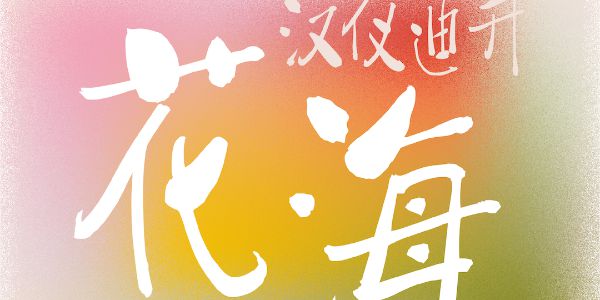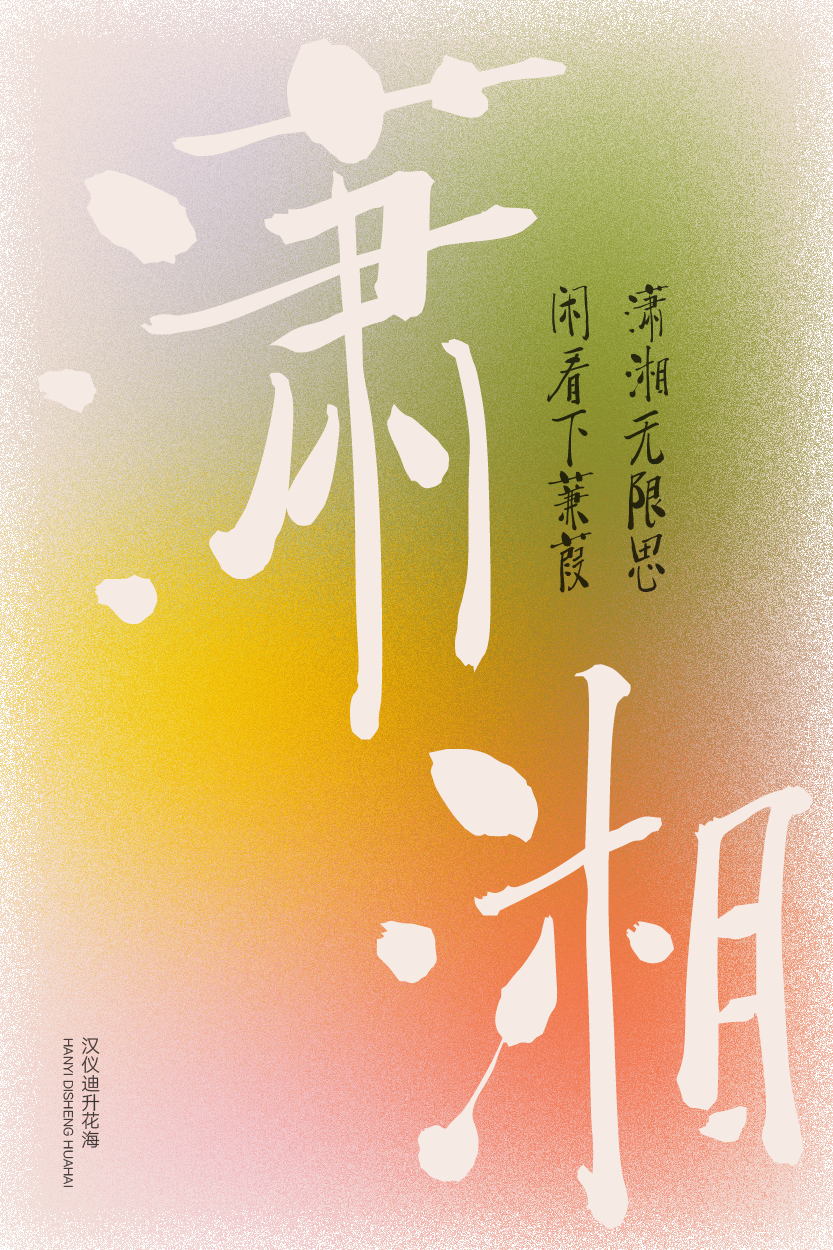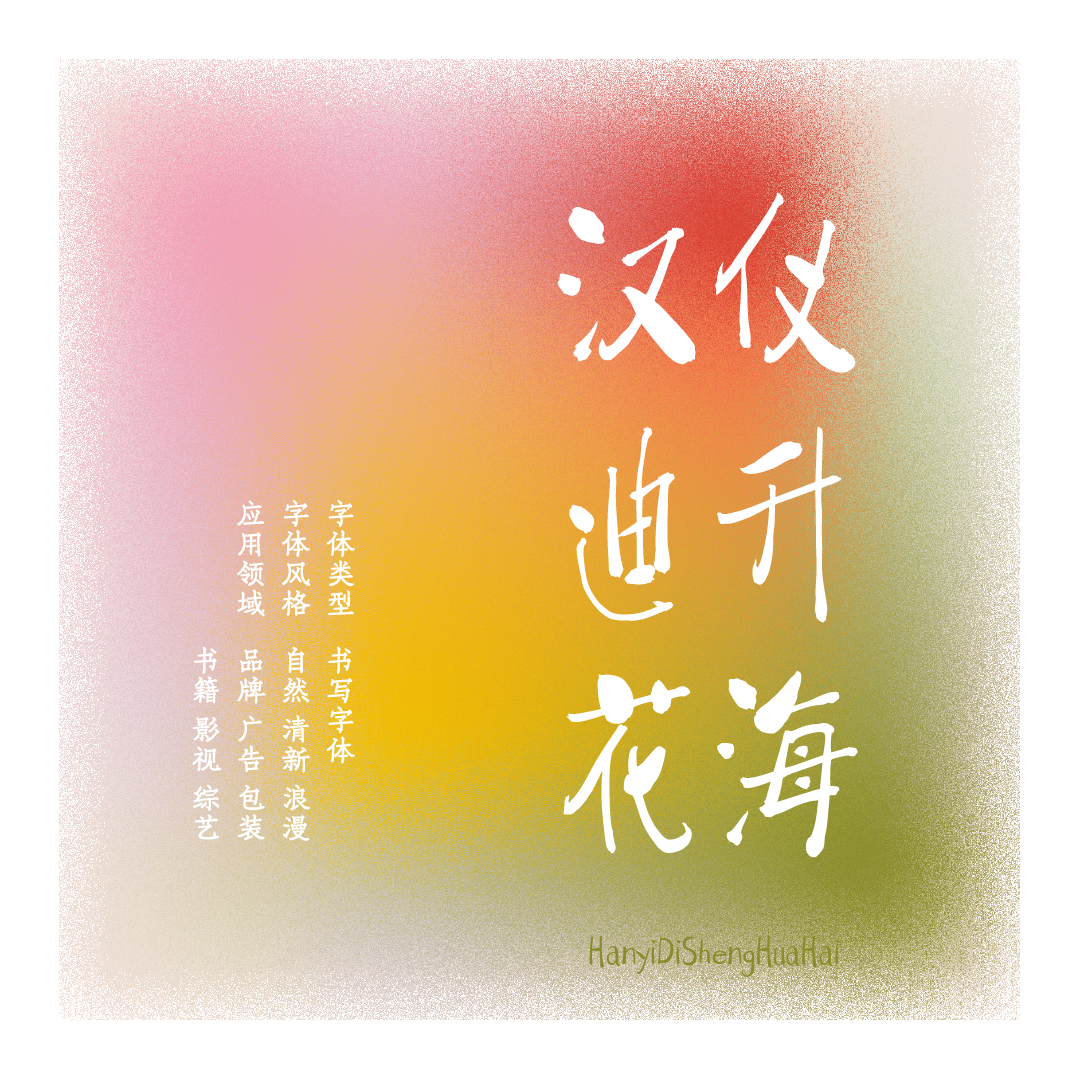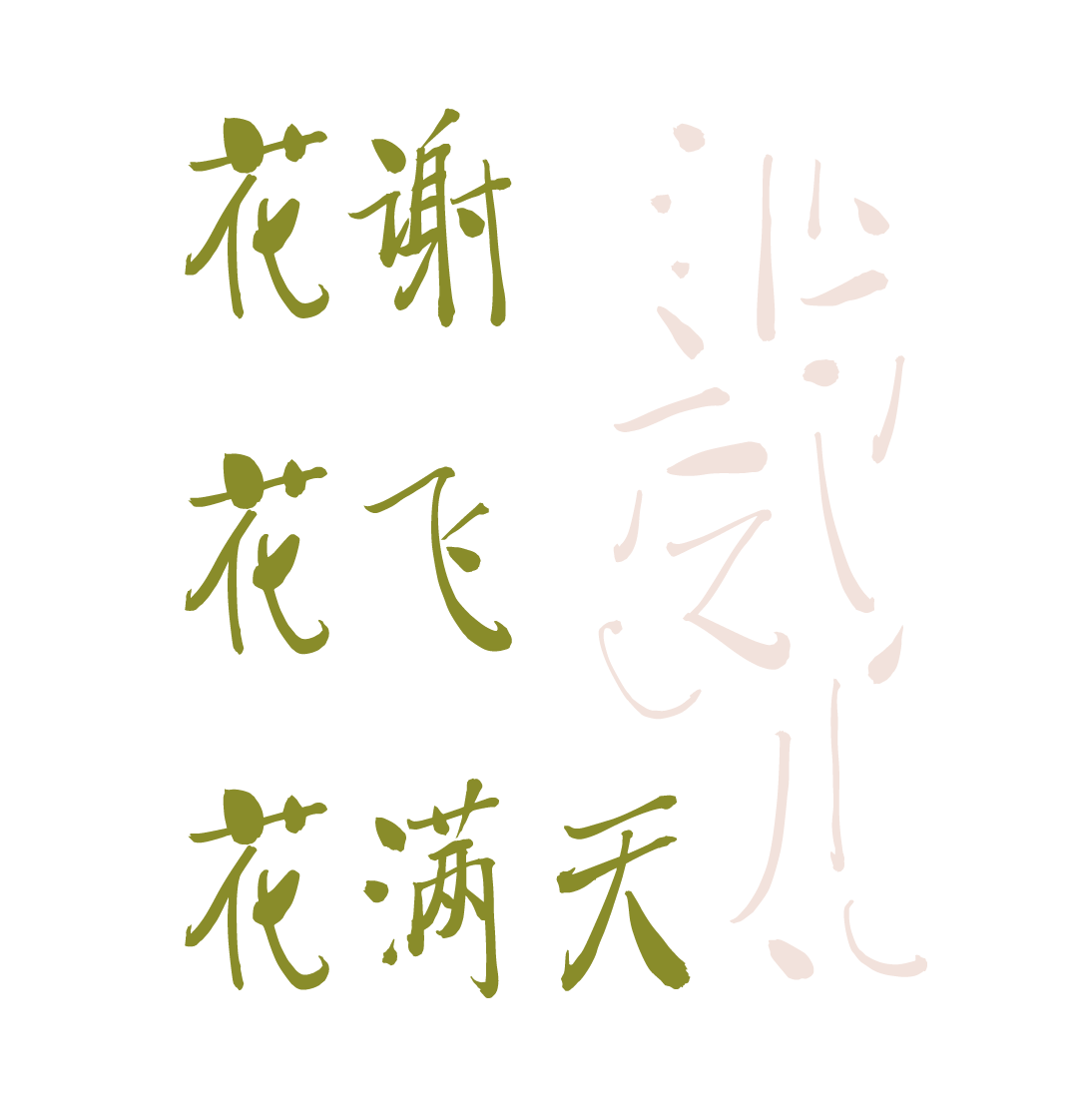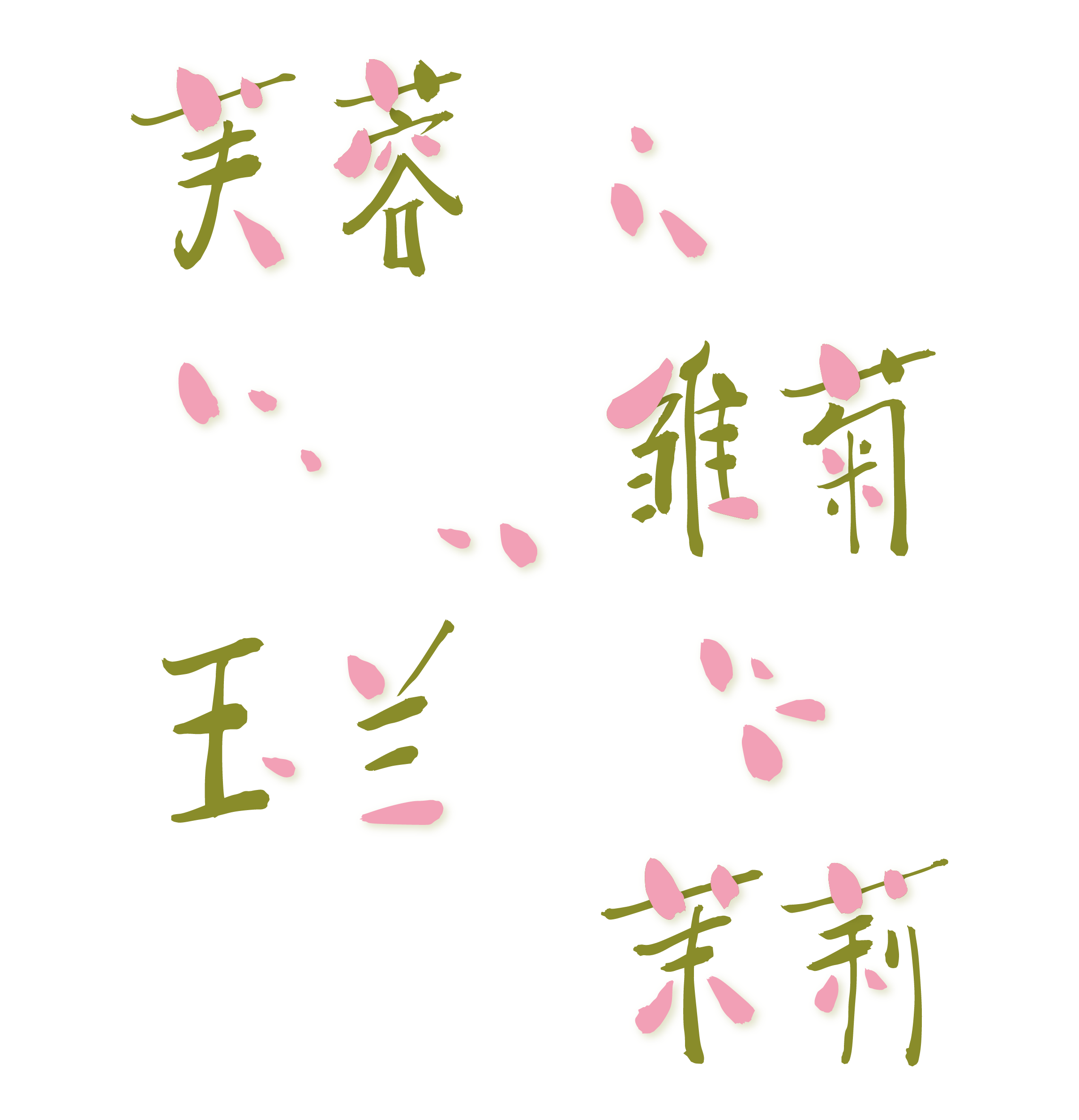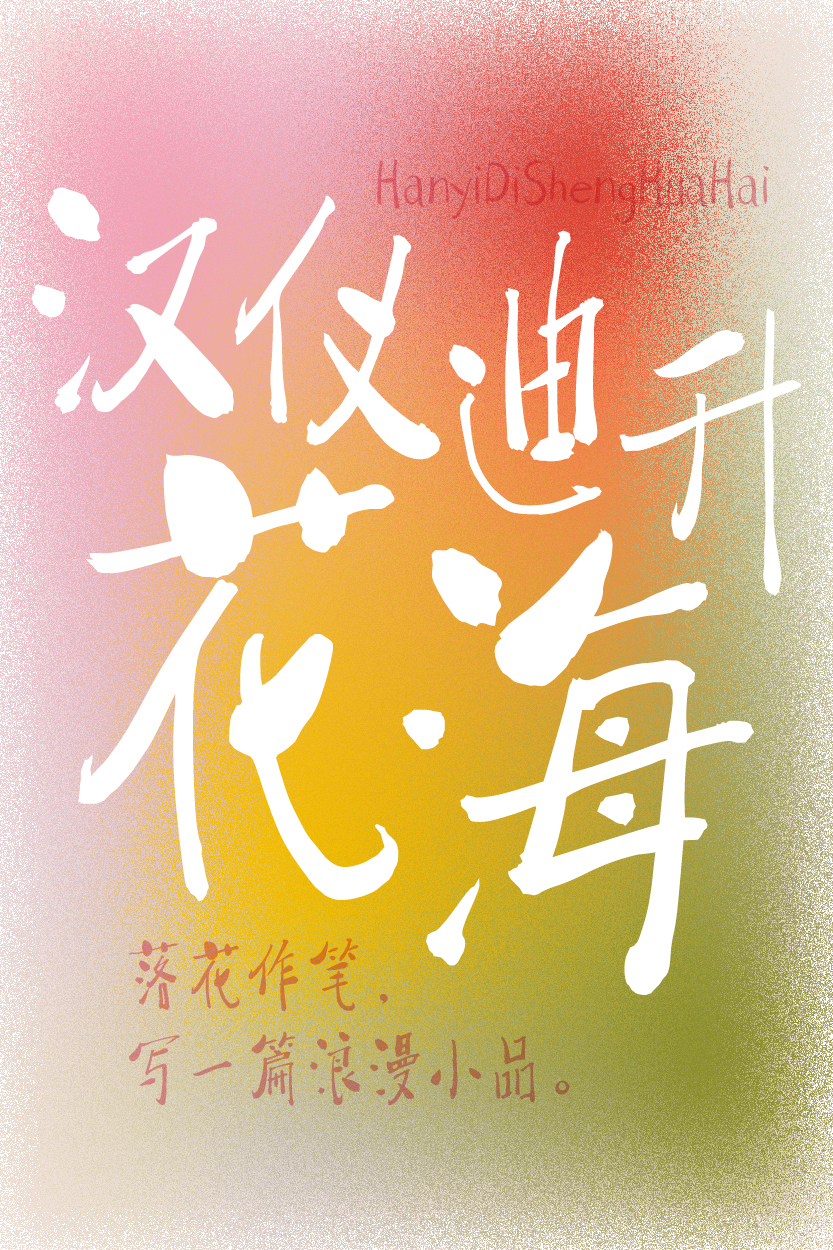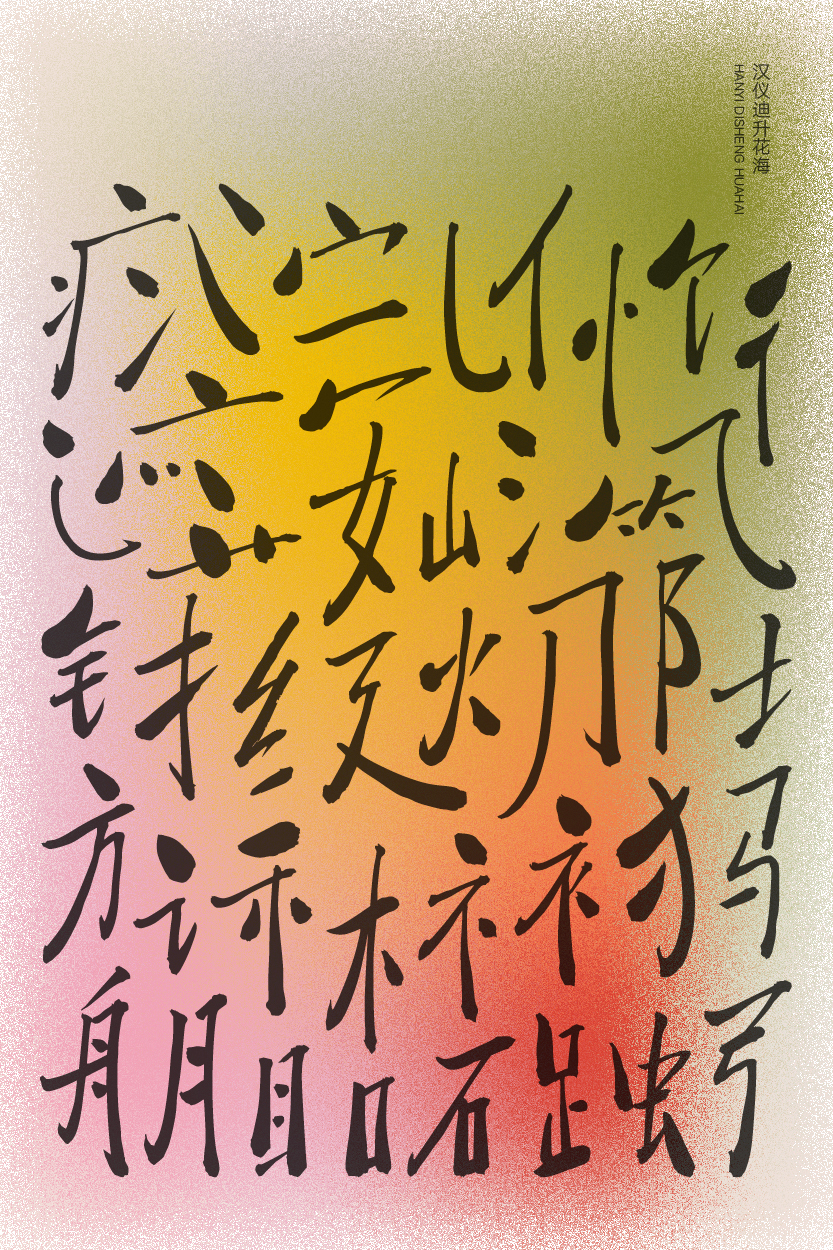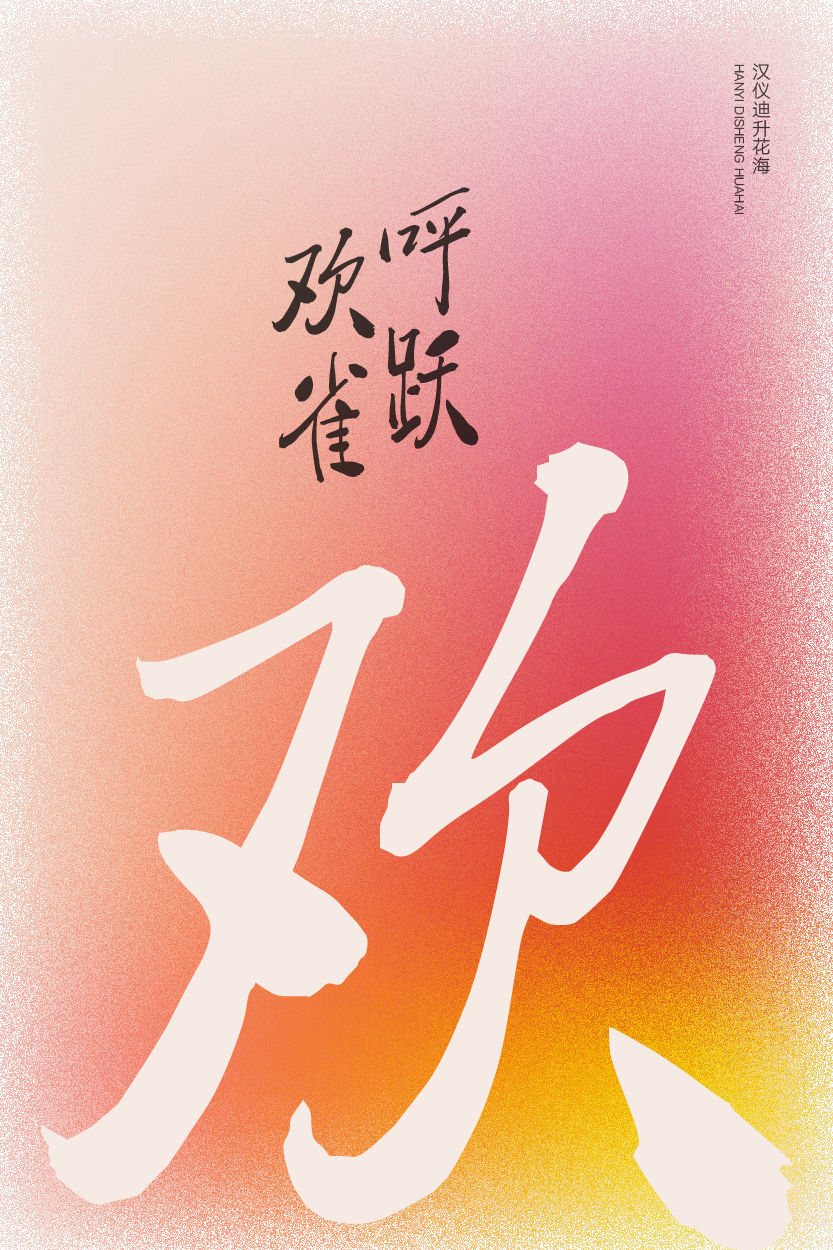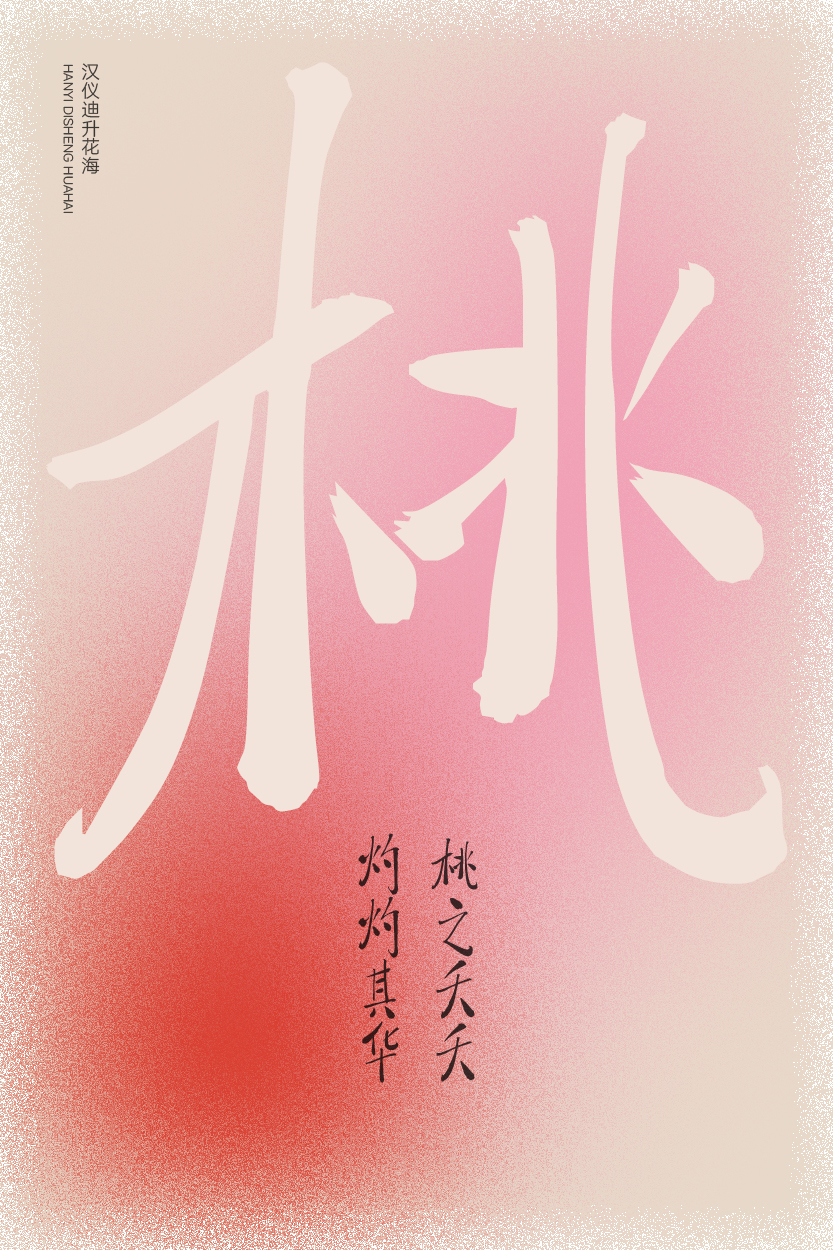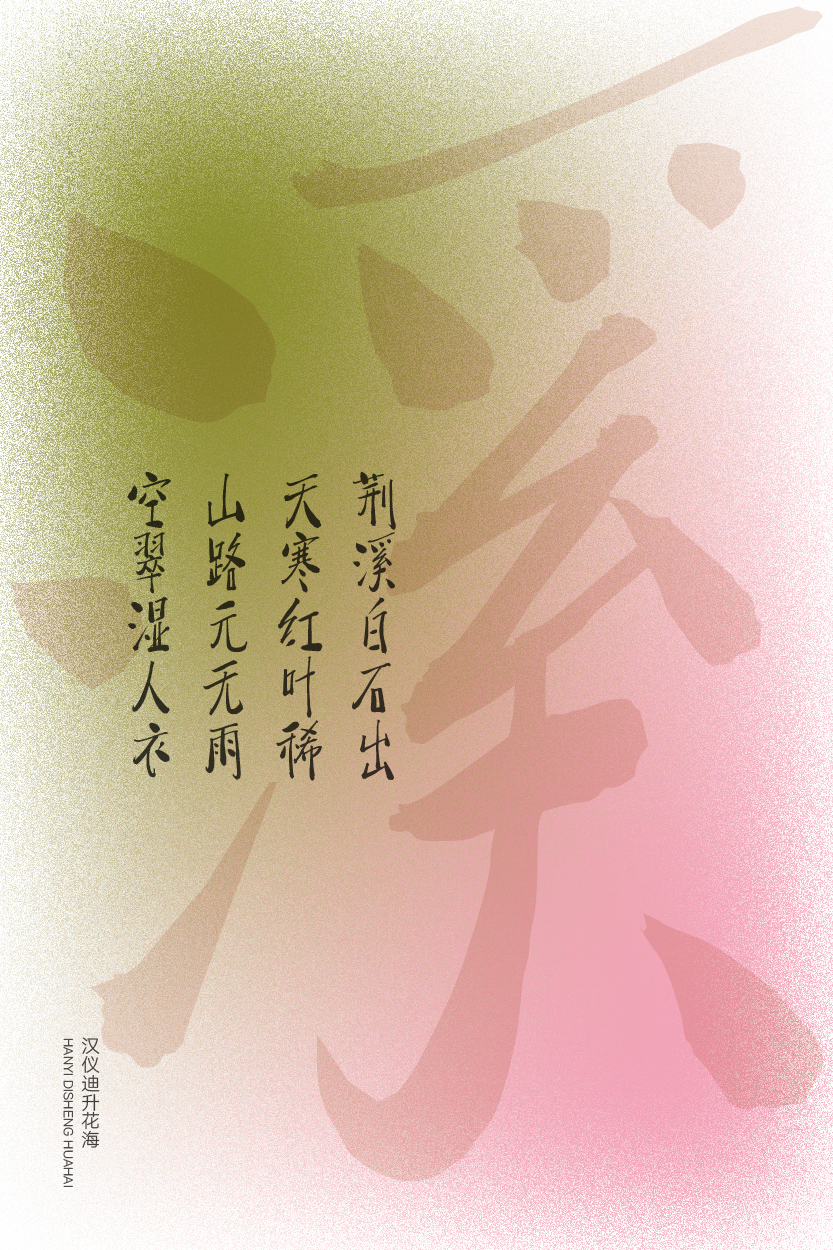
漫天飞舞的多巴胺字体
落花作笔,写一篇浪漫小品。
汉仪迪升花海,由汉仪字库签约作者迪升创作,是一款随笔字体,摆脱了笔法的束缚,随心而作,顺其自然,渲染了落花漫天飞舞的浪漫氛围。这款字体适合用于轻松惬意的使用场景,用于标题字体或少量文本的排版装点其间,给人以置身花海般梦幻的视觉体验。
字形修长、轻盈,适于纵向排版。
笔法随性,摆脱束缚,如落花漫天飞舞。
浓重笔画似花瓣,纤细笔画似花叶。